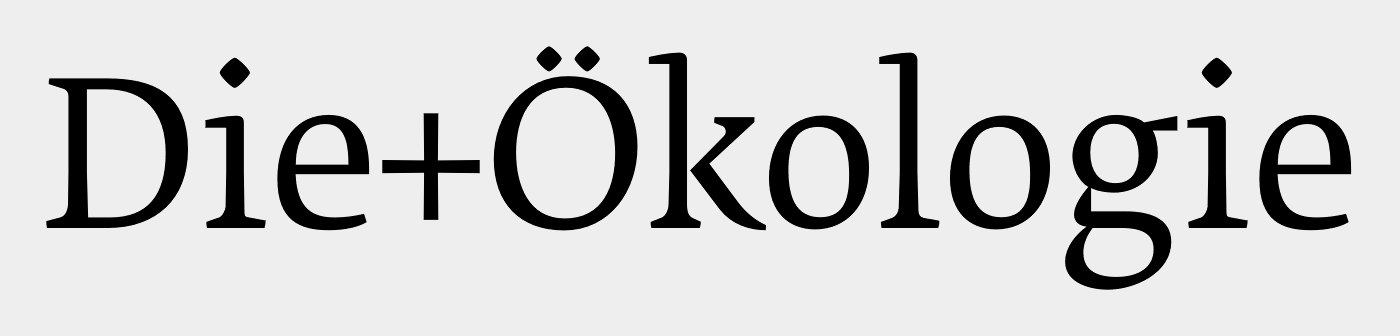
Zeitgemäße Antiqua mit Rauten-Punkten
habe irgendwann diesen screenshot gemacht – keine ahnung, wo –  weil mir die schrift gefallen hat.
erkennt sie wer? (whatthefont kennt sie nicht)
Ja die spricht mich auch immer wieder an. Mit Rauten-Punkten gibt es ja nicht so viele. Das ist die Fedra Serif (den Ober- und Unterlängen zufolge die Version B).
Musst mal schaun, ob es das Ö als Alternative gibt. Vielleicht hat man am Umlaut auch einfach nur gebastelt.